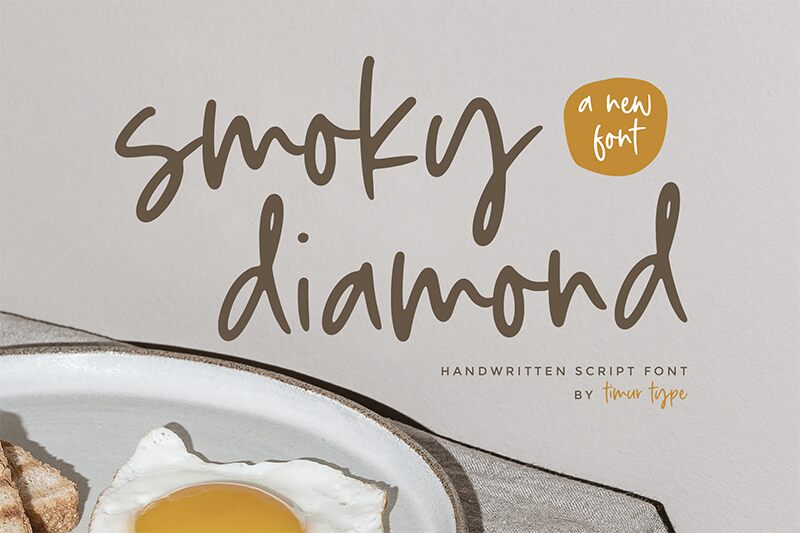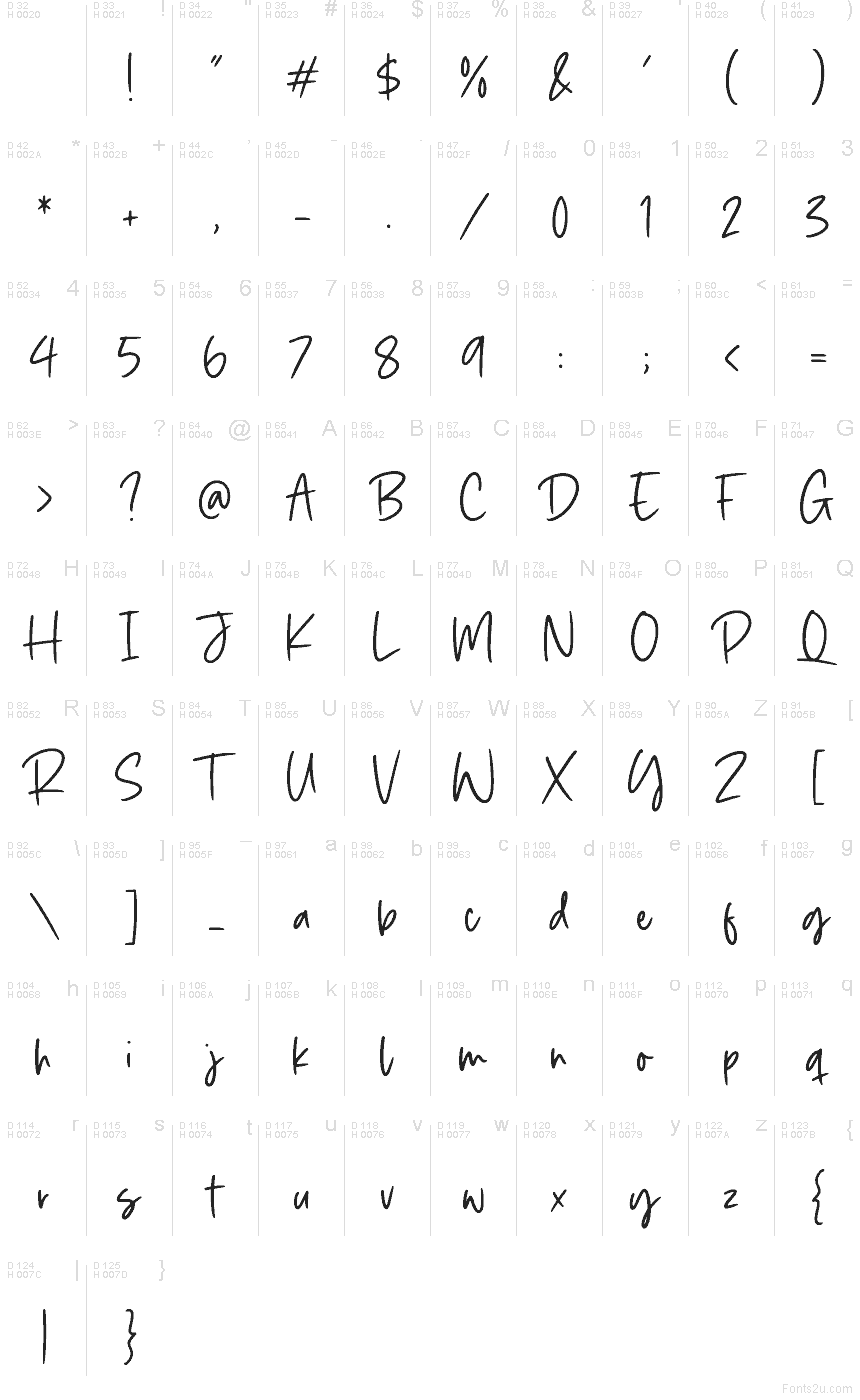
Písmo Smoky Diamond od studia Timur Type Studio je bezplatné ručně psané písmo s volným, plynulým stylem a zaoblenými, propojenými tahy. Písmena se pohybují v uvolněném rytmu, kombinují vysoké, smyčkované iniciály s hladkými spoji a lehce nerovnoměrnou linkou, která působí, jako by byla vykreslena jedním tahem.
Smoky Diamond skvěle funguje v logách, grafice s citáty, příspěvcích na sociální sítě, pozvánkách a obalech, které vyžadují osobní, signaturní nádech. Toto bezplatné písmo se také perfektně hodí na etikety produktů, přání a krátké redakční akcenty, kde jeho neformální styl dokáže nést název nebo frázi, aniž by působilo příliš upjatě.